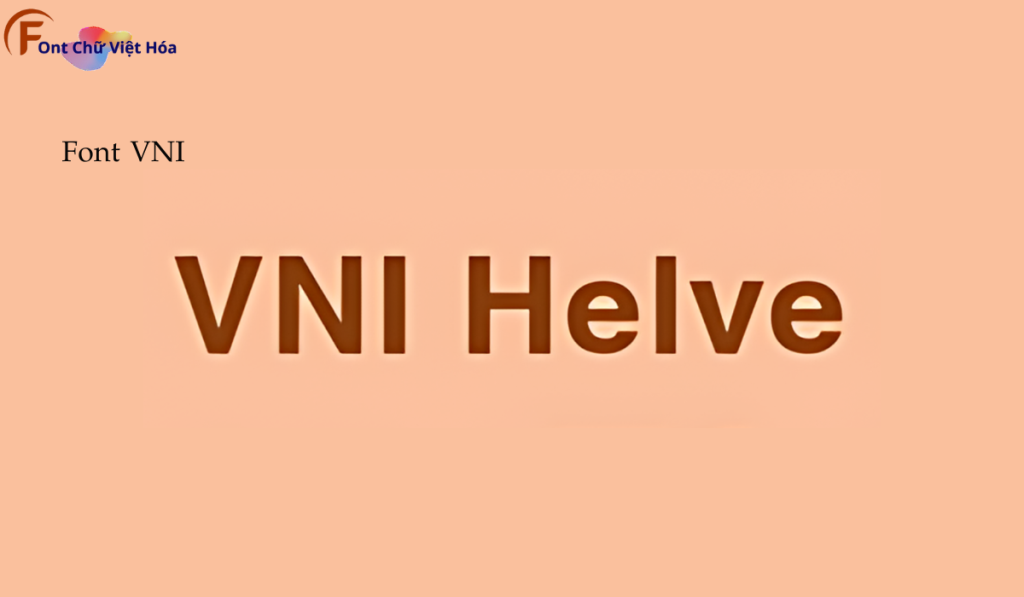
Font VNI Helve Việt Hóa
Tác giả: VNI Helve Việt Hóa
Ngôn ngữ: Vietnamese
Bộ Font: VNI
Phân loại: độc đáo
Kiểu chữ: có chân
Độ dày: Bold, Light, Regular
Font VNI Helve Việt Hóa, thuộc bộ font VNI, mang phong cách hiện đại và thanh lịch, phù hợp cho các dự án thiết kế như thiệp mời, bìa sách, và tài liệu văn phòng. Với các nét chữ không chân và độ dày đều đặn, Font VNI Helve Việt Hóa không chỉ dễ đọc mà còn tạo cảm giác chuyên nghiệp và tinh tế. Việc Việt hóa font giúp người dùng dễ dàng tích hợp vào các thiết kế tiếng Việt, mang lại sự tiện lợi và nâng cao tính thẩm mỹ.